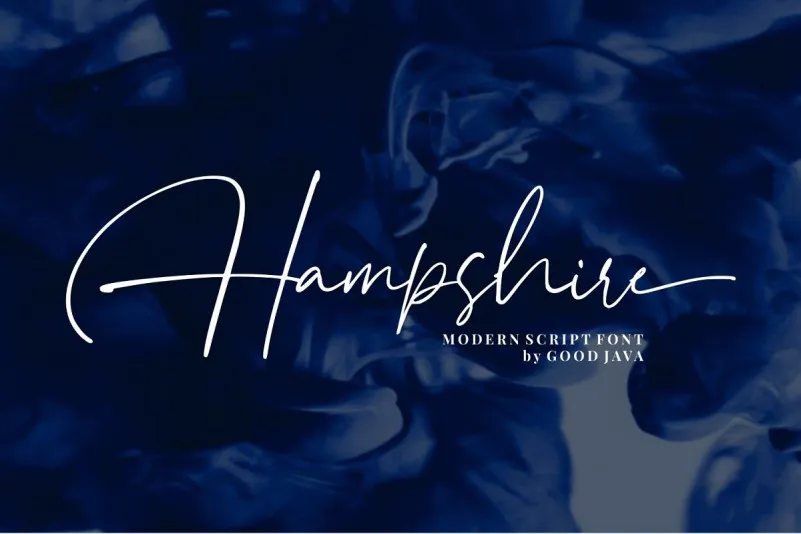
Hampshire Script Font – Download Grátis
Estamos muito felizes por você explorar a Hampshire Font Script! Este é um elegante traçado de script monoline que se torna seu companheiro perfeito para diversos projetos. Seus traços suaves e divertidos são perfeitos para dar ao seu design uma aparência moderna e natural, capaz de destacar em qualquer ambiente. Com a Hampshire Font Script do Good Java Studio, você terá um recurso essencial que se adapta perfeitamente às mais diversas necessidades, desde logotipos e convites até publicações sociais, anúncios, embalagens de produtos, designs de produto, etiquetas, fotografias e até mesmo watermark. Sua versatilidade faz dela uma escolha inteligente para qualquer ocasião especial ou projeto. Não perca mais tempo – é hora de dar vida à sua criatividade com o Hampshire Font Script!